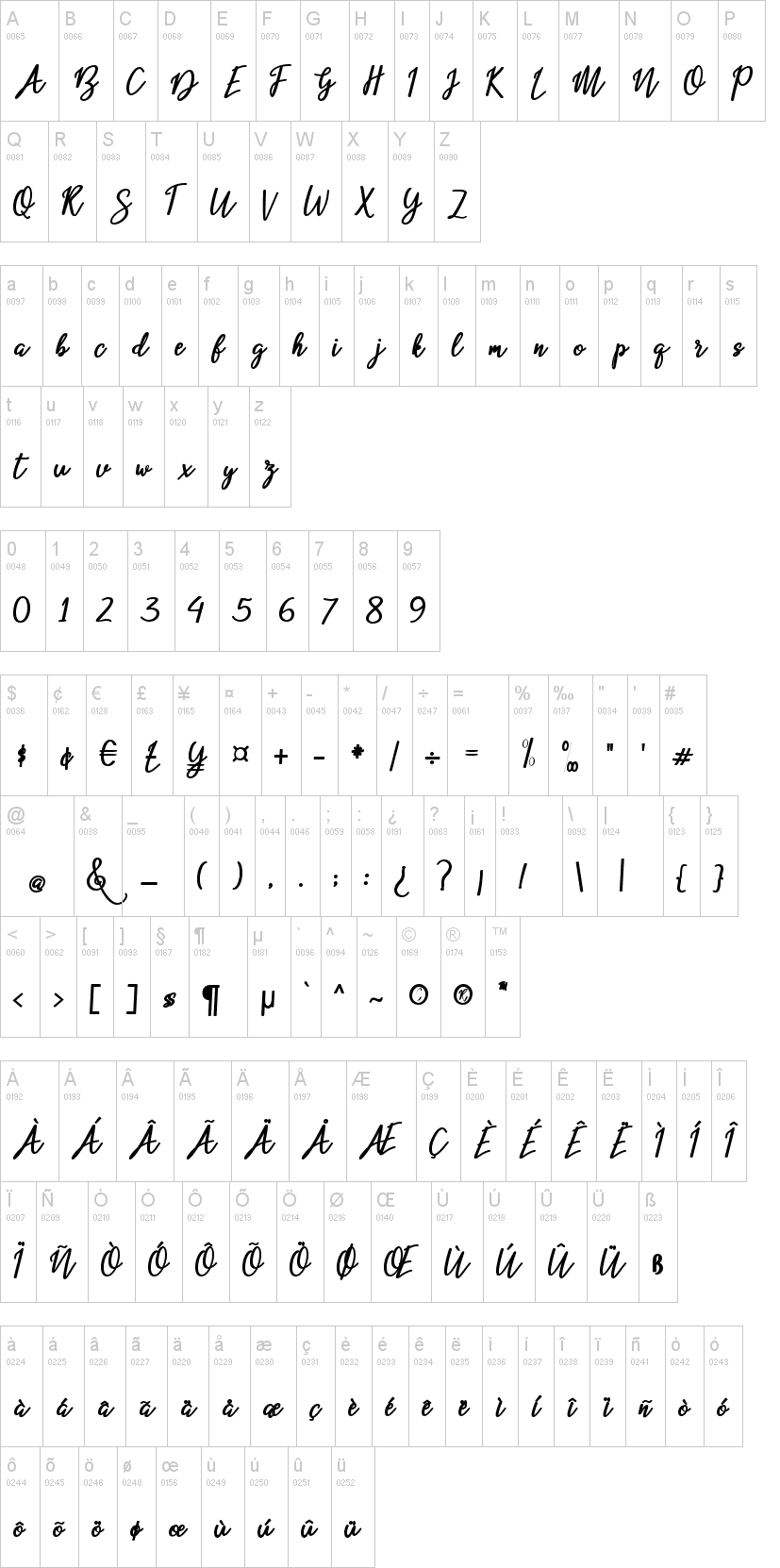
Beloved
Beloved 字体是一款由荷兰设计师 Jan Schmoeger 创作的现代字体。它有着独特的旋律线条,拥有精致的细节和温柔的触感,在字体的设计上结合了传统的技术和现代的设计理念,营造出温暖的空间感。Beloved 字体有着浓浓的浪漫情怀,可以用于贴片、海报、书籍封面等,是一款非常适合用于创作的字体。
Beloved是一款非常不错的手写艺术字体,具有很好的视觉感,适合于文化类的宣传设计、商业类品牌的广告和产品包装设计以及个性化文字排版等较多场景。